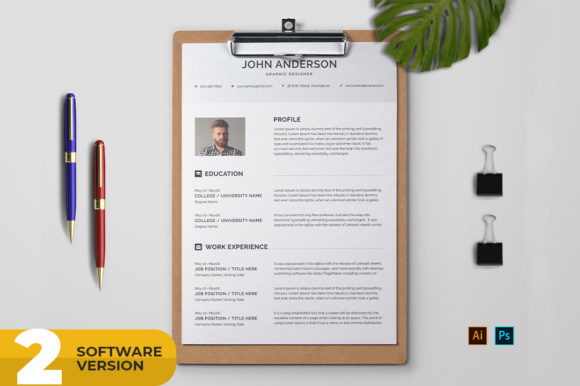
Resume
適切なデザイン要素を見つけるのは難しい場合がありますが、Resumeは作品を即座に引き立てる優れたコレクションを提供します。
精密に作られたResumeは、クリーンなベクター、滑らかなタイポグラフィ、そして安心のための商用ライセンスを提供します。
POD(オンデマンド印刷)製品、結婚式の招待状、またはソーシャルメディアのグラフィックを作成している場合でも、Resumeは理想的です。